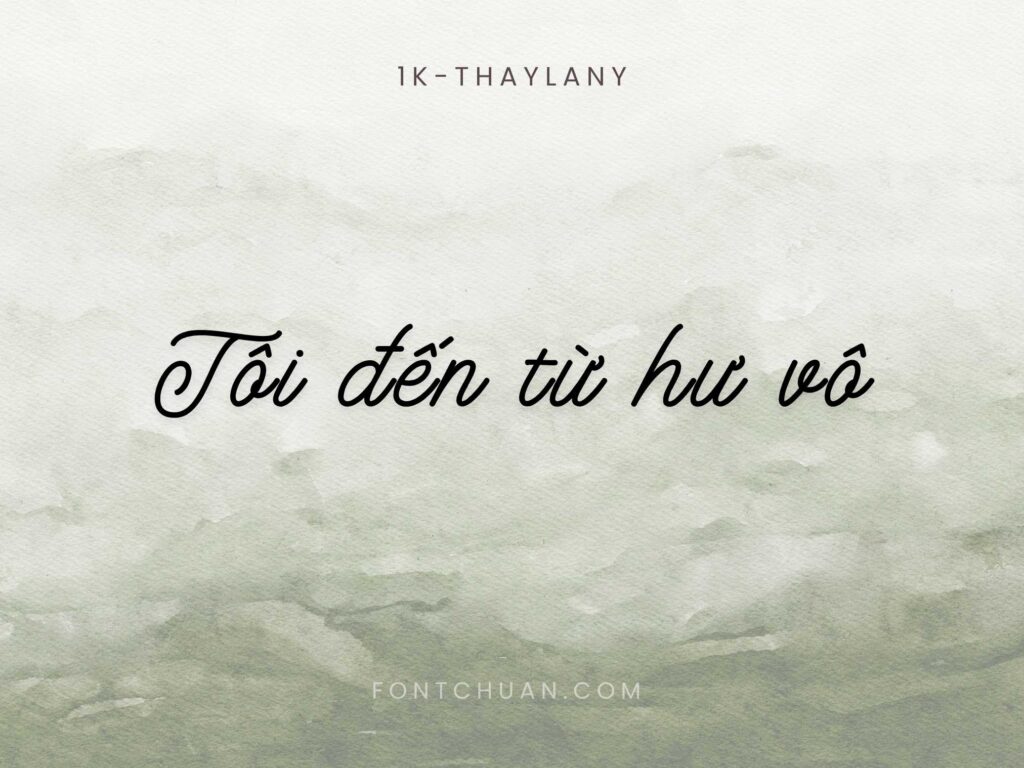
Font 1K Thaylany Việt Hóa
1K-Thaylany là phiên bản Việt hóa của phông chữ Thaylany, được thiết kế bởi Drizy Studio. Đây là một phông chữ monoline script với phong cách viết tay hiện đại, mang lại cảm giác ấm áp và thân thiện cho các thiết kế, đặc biệt phù hợp với chủ đề Giáng Sinh. Thaylany đã được FontTiengViet Việt hóa, hỗ trợ đầy đủ các ký tự tiếng Việt, giúp người dùng dễ dàng áp dụng trong các dự án thiết kế đa dạng. Ngoài tiếng Việt, Thaylany còn hỗ trợ nhiều ngôn ngữ khác, bao gồm tiếng Anh, Pháp, Tây Ban Nha, Đức và Ý. Phông chữ này được thành viên Font Chuẩn sưu tầm và đăng tải nhằm phục vụ nhu cầu sáng tạo phong phú.
Với phong cách viết tay hiện đại và thân thiện, 1K-Thaylany phù hợp cho các ứng dụng như thiệp mời, tiêu đề, logo và các ấn phẩm in ấn cần sự cá nhân hóa. Các ký tự có độ cao trung bình, mang lại sự tinh tế và mềm mại cho văn bản. Font cũng bao gồm các ligatures, giúp tăng tính liên kết giữa các chữ cái, tạo nên sự mượt mà trong thiết kế. Nhờ sự linh hoạt và hiện đại trong hình thức, 1K-Thaylany còn có thể được sử dụng như một Font chữ công nghệ, phù hợp cho các giao diện số, tài liệu kỹ thuật hoặc các dự án thiết kế công nghệ, vừa đảm bảo tính thẩm mỹ vừa dễ đọc.